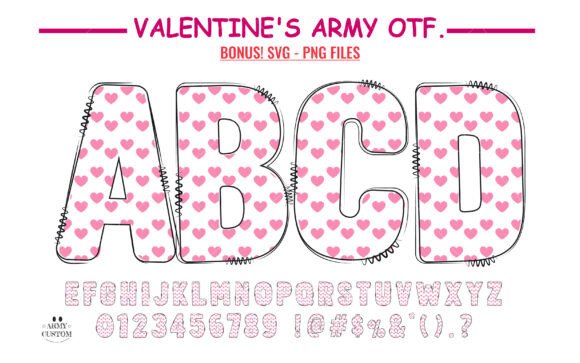
Love Valentine's Doodle Hearts
Doğru tasarım öğelerini bulmak zor olabilir, ancak Love Valentine's Doodle Hearts, çalışmanızı anında bir üst seviyeye taşıyan olağanüstü bir koleksiyon sunar.
İster İsteğe Bağlı Baskı (POD) ürünleri, ister düğün davetiyeleri veya sosyal medya grafikleri oluşturuyor olun, Love Valentine's Doodle Hearts ideal bir uyumdur.